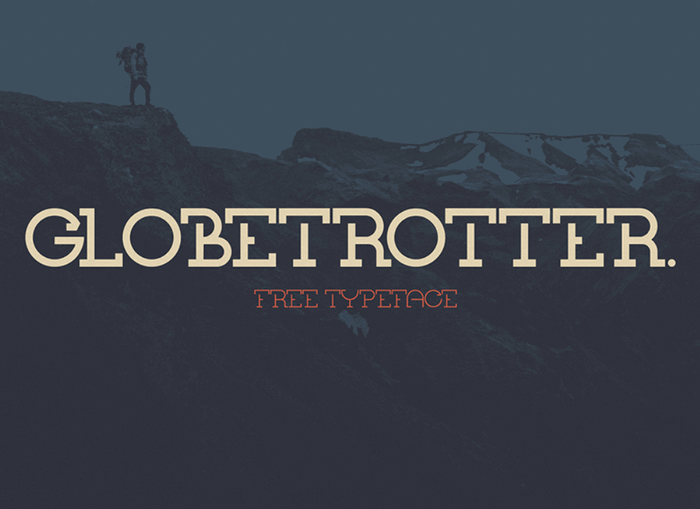
Globetrotter Typeface – Download Grátis
Globetrotter Typeface é uma elegante tipografia slab serif que oferece uma solução perfeita para seus projetos de design. Desenhada pelo Zains e compartilhada por Samuel Salminen, esta fonte combina uma simplicidade robusta com um encanto moderno, fazendo-a óbvia para ser usada tanto em logotipos quanto em embalagens de produtos, cabeçalhos, panfletos, materiais de merchandising e até mesmo nas redes sociais. Suas linhas sólidas e harmoniosas proporcionam uma aparência clara e profissional que se adapta perfeitamente a diversos estilos de design. Adquirindo Globetrotter Typeface, você adicionará mais um tesouro à sua coleção de fontes. Este é o tipo certo para criar identidades visuais fortes e memoráveis, especialmente em ambientes onde a simplicidade pode trazer elegância. Seja na criação de uma nova marca, no desenvolvimento de embalagens criativas ou na produção de materiais promocionais deslumbrantes, Globetrotter Typeface oferece o tom certo para dar um toque único e moderno a seus projetos.